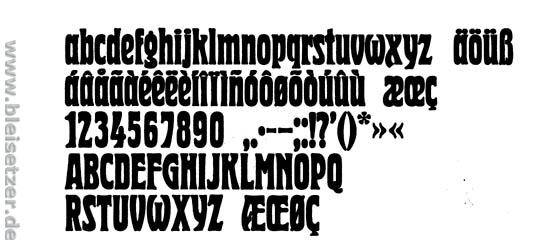
Schrift für Flouristikgeschäft (Jugendstil)
Ich suche die passende Schrift für ein Flouristikgeschäft. Ich soll dafür eine Imagebroschüre (rein Typographisch) erstellen, das ganze soll aussehen wie im Jugendstil.
Wer kann mir helfen? Welche Schrift wäre fürs Logo und welche für den Fließtext? Freu mich auf die Antwort, lg Radiomoderator
Ja, klar:
Und Jugendstil-Schriften gehören zum Schönsten, was wir kennen:
Herold Reklameschrift
H.Berthold AG, Berlin
Erstguß 1904
Hermann Hoffmann
Au ja, hey, hübsch.. die Seidel'sche Schrift.
304_boecklin_1.jpgArnold Böcklin, ein Klassiker mit floralen Formen.
In Esslingen fungiert sie für das Merkelsche Jugendstilbad.